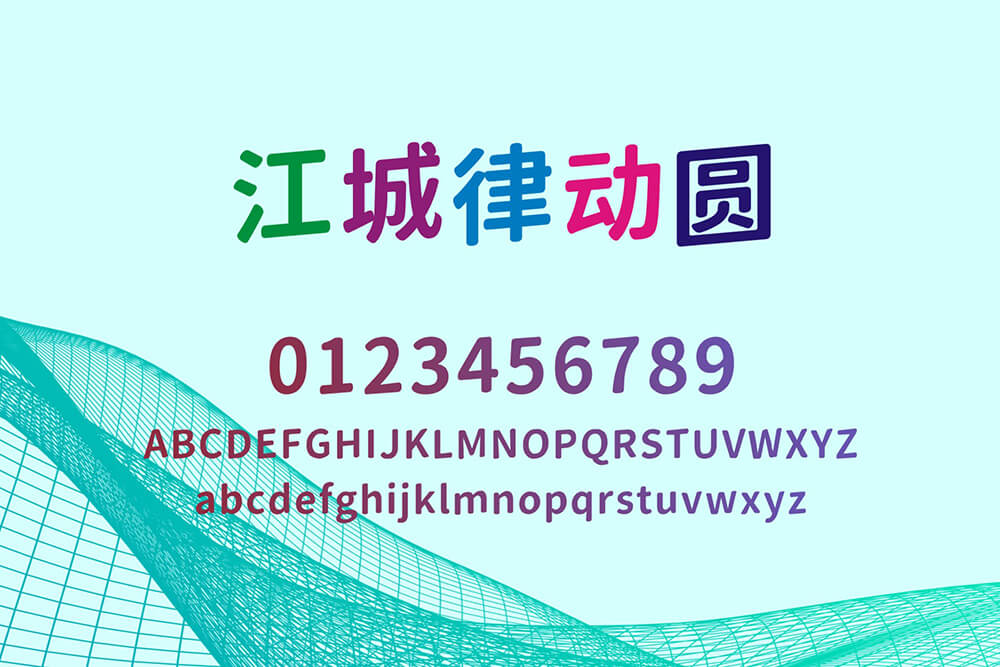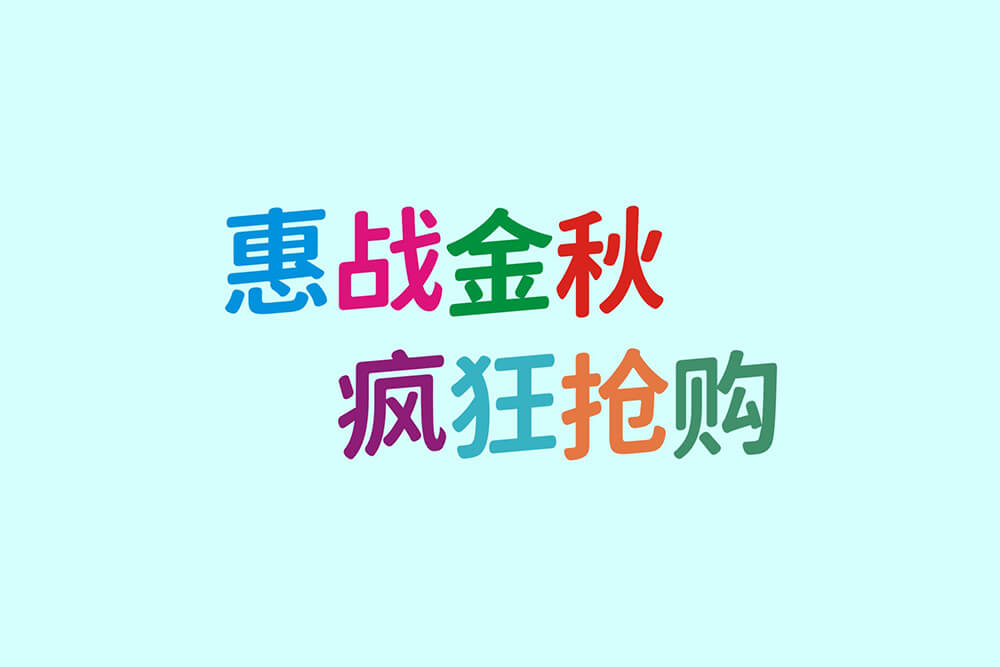
江城律动圆由设计师刘鹏基于狮尾圆体 SC-Bold 改造而成的一款免费可商用圆体字体。作者在保留圆体的柔和、可爱、亲和力强的特点基础上,将字形整体向上倾斜约 5 度,使其具有了独特的律动感和视觉吸引力。
江城律动圆涵盖 6763 个简体汉字、英文、数字及常用符号。笔画粗壮,识别度高,自带活动促销的 BGM感,非常适合用于活动、促销等广告语,适当缩小字间距效果还会更佳。